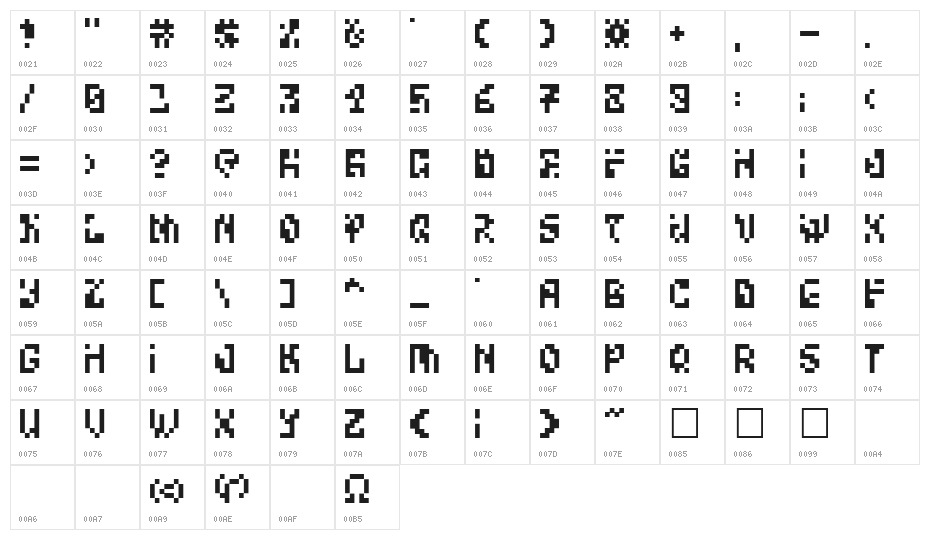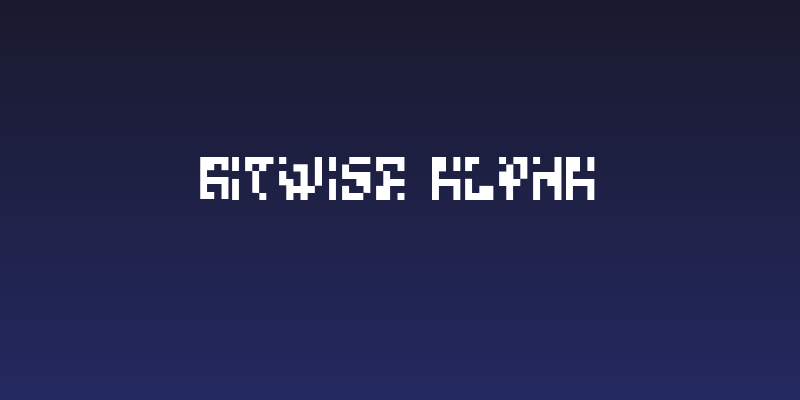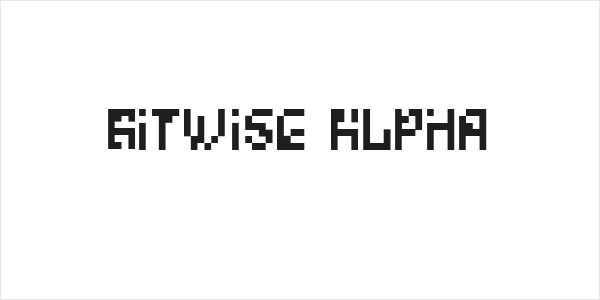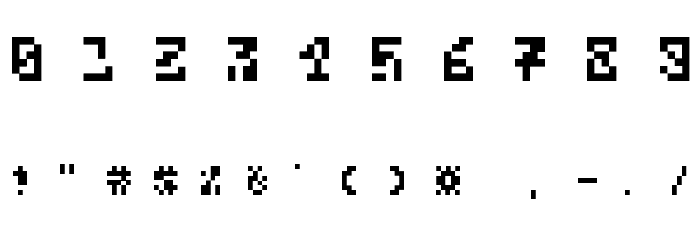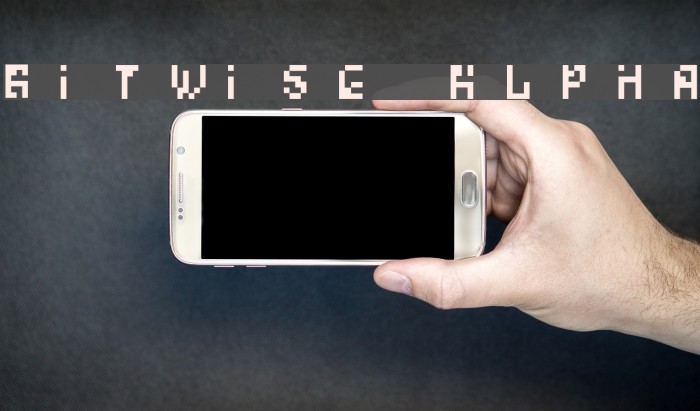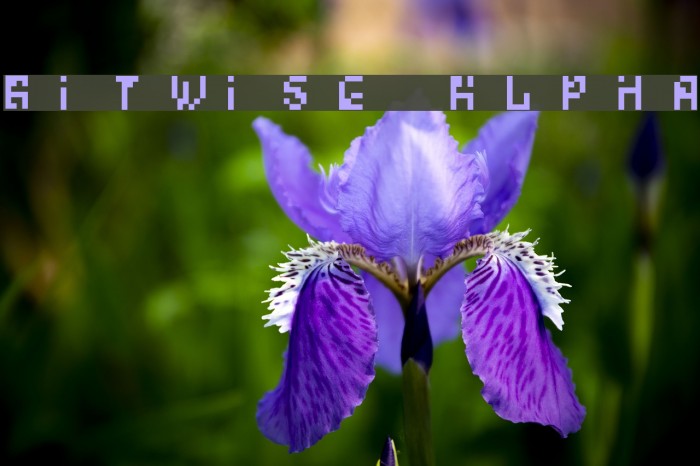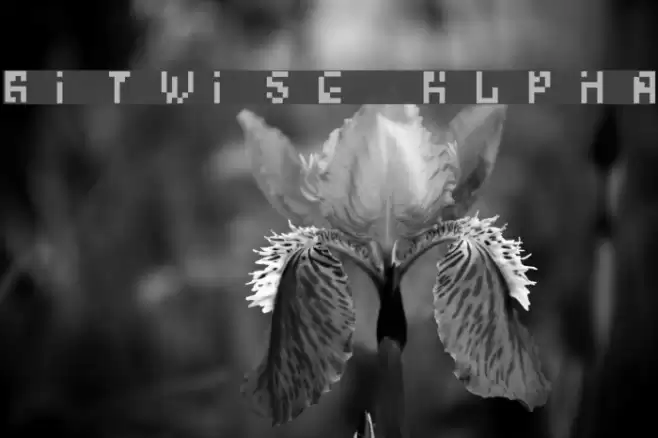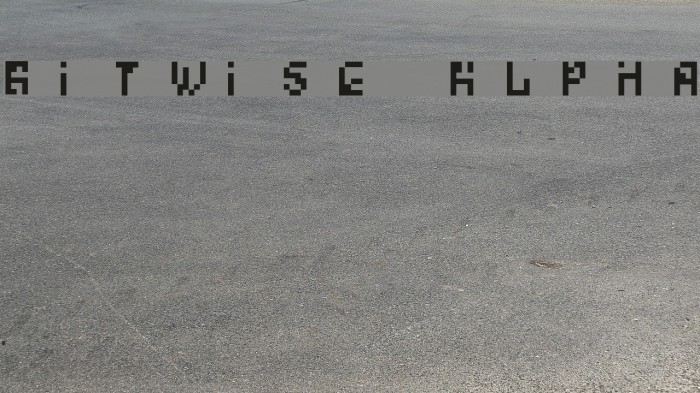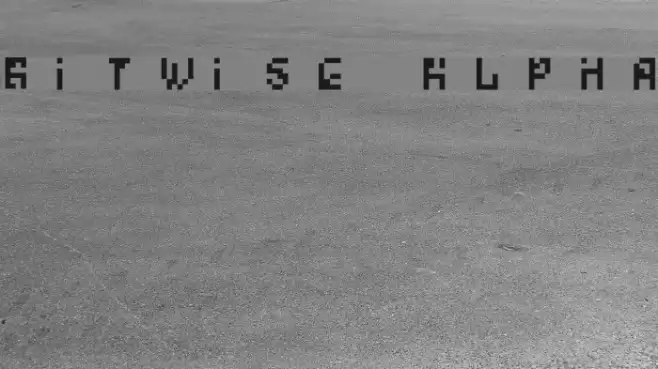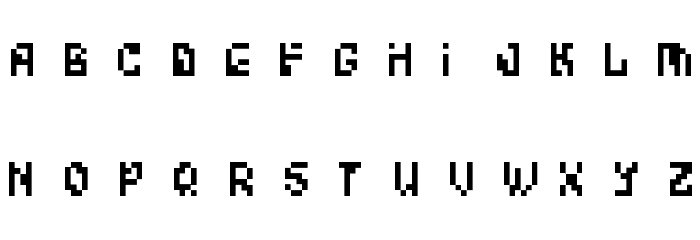
Bitwise Alpha Font
| Style général | Retro, Digital |
| Cas d'utilisation | Headlines, Logos, Digital interfaces |
| Projets proposés | Ideal for retro video games, digital art projects, tech-themed designs, and any creative work that requires a nostalgic digital look. |